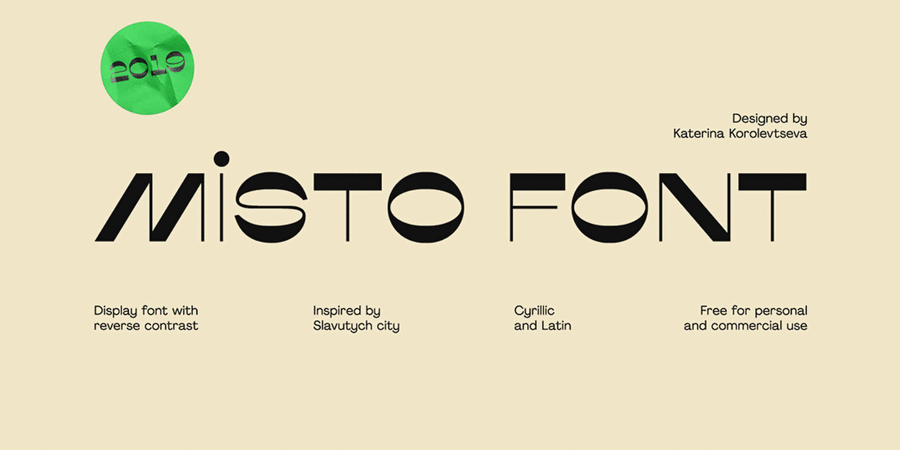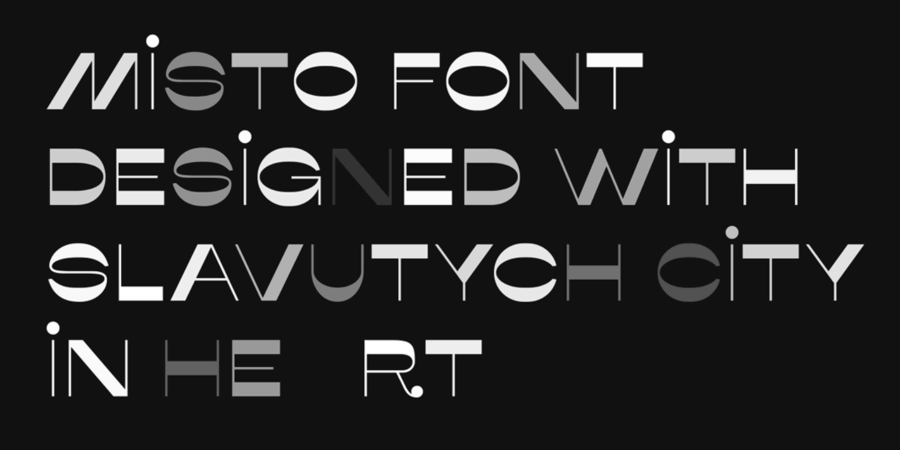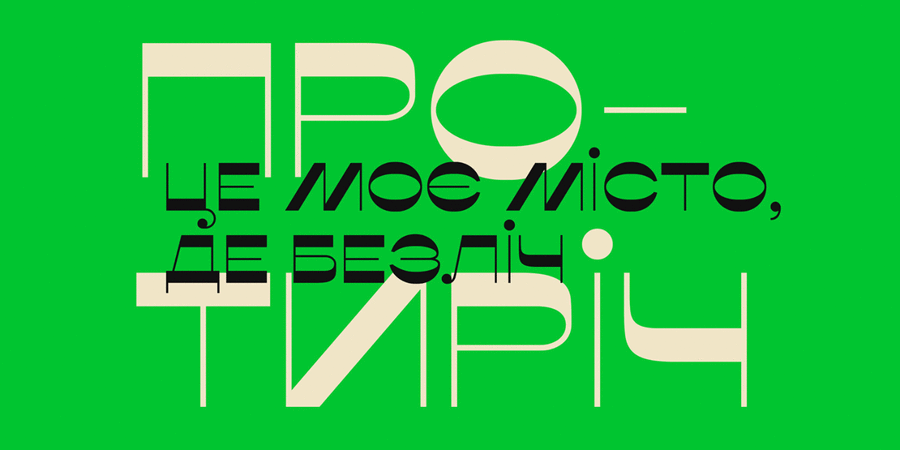
Шрифтова пара з Kamila Regular (1 з 4)Опис шрифта Misto FontШрифт Misto Font був натхненний Славутичем, але розроблявся не спеціально для цього міста.
Славутич – наймолодше місто України. Його зводили після трагедії на Чорнобильській АЕС як місто-мрію, місто-утопію. Для будівництва об’єдналися 8 тодішніх республік СРСР і справилися в рекордні строки. Місто поділене на 13 кварталів: Вільнюський, Єреванський, Київський та інші. Кожен відображає унікальну архітектуру і колорит країни, яка його будувала. Це місто постмодерністської архітектури, п'ятиповерхівок, високих сосен, за якими не видно будинків, відсутності візуального шуму і міського транспорту. Його іноді називають місто в лісі й ліс у місті.
Шрифт має зворотний (протилежний) контраст, а Славутич – повна протилежність великим метушливим містам. Нестандартні широкі пропорції, на які надихнули низькі 5-поверхові будинки й особливо ФОКи (фізкультурно-оздоровчі комплекси). Вони практично скрізь однакові, хоч архітектура кварталів різна. Краплі в деяких літерах і виносних елементах, круглі діакритичні знаки – найхарактерніша деталь цього шрифту, яка відображає молодий характер міста. На неї наштовхнула буква «Й» на вивісці музею.
Асоціації з сімейством шрифтів Misto FontОсобистість і характер гарнітури:
сучасний, дитячий, наївний, милий, артистичний, весняний, святковий, свіжий, добрий, зелений, музичний, ритмічний, неформальний, грайливий, веселий, емоційний, радісний, цікавий, оригінальний, вільний, задерикуватий, енергійний, характерний, привітний, живий, прикольний, доброзичливий, добродушний, вигадливий, смішний, самобутній, неординарний, мажорний, інфантильний, легковажний, небувалий, хитрий, динамічний, дивний, усміхнений, щасливий, творчий, симпатичний, екзотичний, міський, молодіжний, точний, модний, тусовочний, дотепний, іронічний, потішний, помітний, яскравий, виразний, театральний, демонстративний, експериментальний, вінтажний, естетський, претензійний, екстравагантний, нонконформістський, богемний, манірний, мінливий, оманливий, епатажний, сексуальний
розваги, прикраса, Місто, аксесуари, перукарня, сувенір, клумба, гра, відпочинок, табір, весна, свято, подарунки, магія, цукерки, музика, літо, канцтовари, дитяча книжка, пригоди, анімація, мультфільм, день народження, одяг, канікули, гумор, дизайн, тусовка, вечірка, коктейль, бар, кінотеатр, атракціон, телебачення, шоу, алкоголь, туризм, кіно, цирк, ярмарок, реклама, театр, взуття, фокусник, ресторан, комедія, кафе, Інстаграм, дискотека, аквадискотека, графіка, ілюстрація Гарнітура асоціюється з віком: